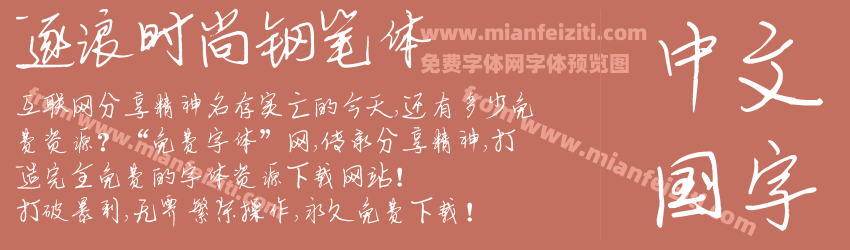
逐浪时尚钢笔体
作品设计背景与理念
虽然是钢笔体,其实整个创作是在微软公司的Surface Pro3的触屏设备上写作完成,并进行矢量导入制作,最终合成整个字库。字体设计原则力求符合当代人的审美规则,支持2k4k高分辨率显示的电脑字体显示。
逐浪时尚钢笔体,既有源自上个世纪末期的庞中华硬笔书法之精髓,又融合了现代美术设计、电子创作的精华,清新隽永,线条柔软,是现代硬笔字库的最佳选择。
本款“逐浪时尚钢笔体”是一款书写很新颖的字体,字体大方,适合各种设计作品使用!欢迎下载!